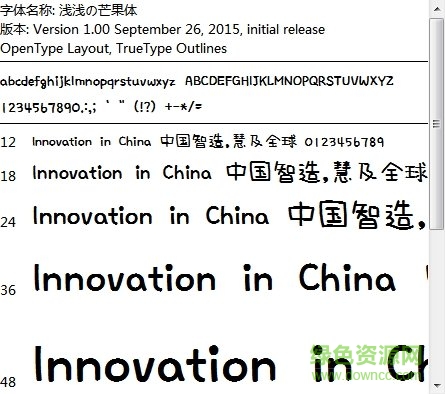
芒果字體ttf
芒果體ttf是淺淺美化修飾的一款非常清新自然的水果類藝術(shù)字體,字形有著卡通字體的童真童趣,結(jié)構(gòu)勻稱有著極佳的藝術(shù)效果,喜歡的朋友就來綠色資源網(wǎng)試試吧!
芒果字體ttf特色
芒果字體類似卡通字體,但并沒有多余的修飾和點(diǎn)綴物,還原文字本身的清爽體驗,通過別致的造型顯得十分生動活潑。